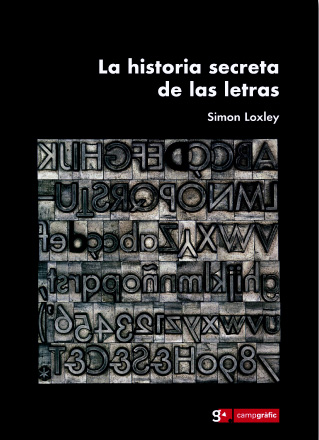
La Historia Secreta de las Letras
Simon Loxley (2007)
Campgràfic
Para los apasionados de la tipografía, para quienes valoran el trabajo detrás del diseño de una fuente con sus cientos de glifos y donde cada uno expresa de forma gráfica el sonido cotidiano, el libro de Loxley les proporcionará momentos deliciosos. El autor, nacido en Inglaterra es tipógrafo, diseñador y profesor publica su primer libro recuperando un anecdotario delicioso sobre las vidas privadas de las tipografías y, por supuesto, de sus autores.
En este libro podemos encontrar la triste historia de Goudy, diseñador de la vilipendiada fuente Cooperplate, quien vio su imprenta y trabajo consumidos por el fuego en dos ocasiones; el misterioso inicio de los tipos móviles en la lejana China y cómo fue que Gutenberg lleva el laureado título de creador de la imprenta. Poco se sabe de este personaje; no existe una fecha exacta de su nacimiento, así como retrato de su efigie. Pese a esto, aún se conservan documentos legales que harían las delicias de una revista de chismes actual: idas y venidas, unión y disolución de sociedades; muertes por peste, demandas y robo de proyectos misteriosos son parte de la apasionante historia de la imprenta. Más adelante, podemos adentrarnos en las vicisitudes de William Caslon, personaje del siglo XVII que, en una Inglaterra convulsa, solo estaba permitido tener imprentas en Londres a excepción de las universidades de Oxford y Cambridge por no mencionar el permiso para diseñar tipos, Caslon logró crear una de las industrias más prósperas en el ámbito de la imprenta y heredó su imperio a su hijo y nuera, quien fuera pionera en la administración de un negocio eminentemente masculino. En el capítulo 4, podremos disfrutar de la «extraña vida de ultratumba» de John Baskerville ya que el autor nos lleva de la mano a un recorrido a lugares como cementerios perdidos o iglesias centenarias, en donde una mañana se recuperaron los restos del mencionado tipógrafo, justo en donde nadie creía que habría alguna tumba. La historia del recorrido de los huesos de Baskereville es bastante peculiar.
En resumen, este libro es una delicia porque nos enteramos de datos que no encontraremos fácilmente de nuestros tipógrafos favoritos, algunos realmente perturbadores, pero que no dejan de humanizarlos y traerlos a la vida a través de su obra. Si eres amante de la historia, del diseño y la investigación, este libro es para ti.